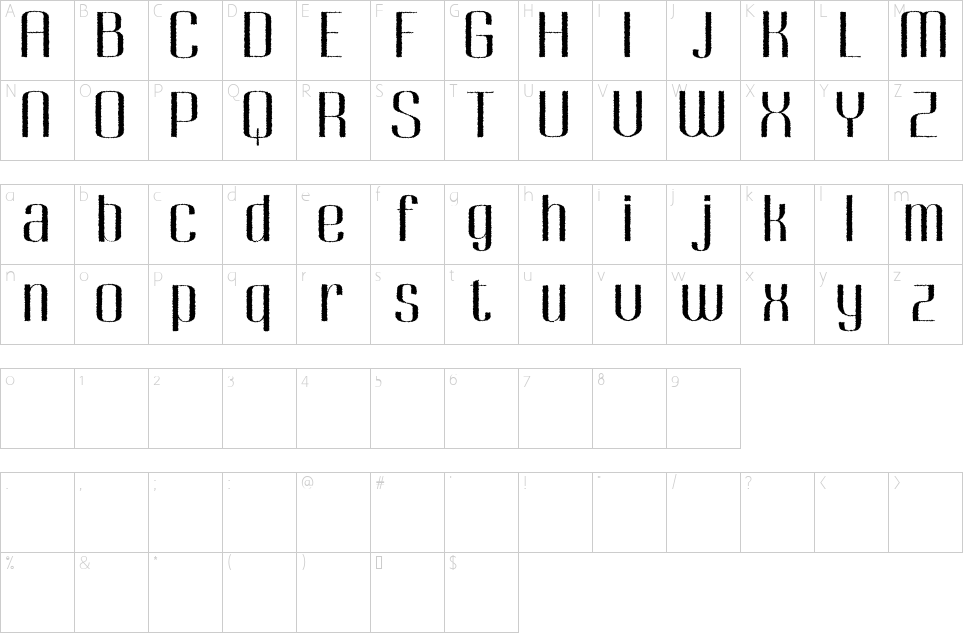
Dazney Rough Font – Download Grátis
A Dazney Rough é uma fonte robusta e autêntica que traz os melhores traços do design industrial. Esta fonte foi criada pela Craft Supply Co, empresa conhecida por suas soluções de personalização de logotipos e materiais de desenho gráfico. Com um estilo moderno e semicorporativo, a Dazney Rough é ideal para criações em ambientes profissionais ou comerciais que exigem uma aparência sóbria e eficiente. Suas linhas definidas permitem uma tipografia poderosa que se destaca tanto em elementos de marca quanto em documentos técnicos ou projetos gráficos industriais. Com seu design robusto, a Dazney Rough oferece um excelente equilíbrio entre força visual e legibilidade, tornando-a uma fonte perfeita para quem busca um estilo único para seus materiais digitais. Com apenas 46 downloads totais, você pode desfrutar desta font gratuita para Windows e Mac sem preocupações de direitos autorais.